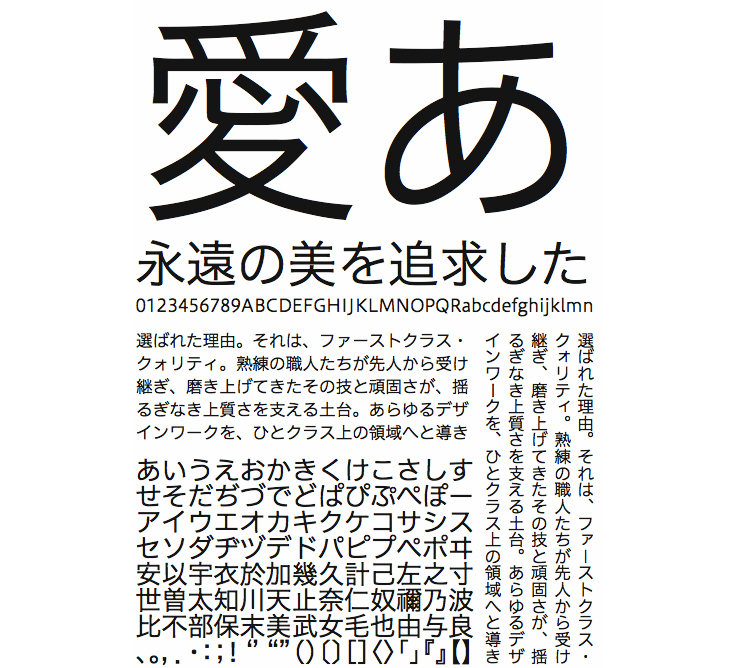
【ヒラギノUD角ゴF】「ヒラギノ角ゴ」の基本デザインを受け継ぐユニバーサルデザインのフォントです。仮名に「ヒラギノ角ゴ AD 仮名」を採用。文字の美しさはそのままに大きさを整えることでくっきり・すっきりとしたラインを提供。濁点・半濁点の強調、数字・欧文のオリジナルデザイン採用により判読性を向上。本文・見出し、組込み、サイン、TVテロップなど広い用途に対応。縦組でも横組でも美しい組版を実現します。
ヒラギノUD角ゴF StdN W3